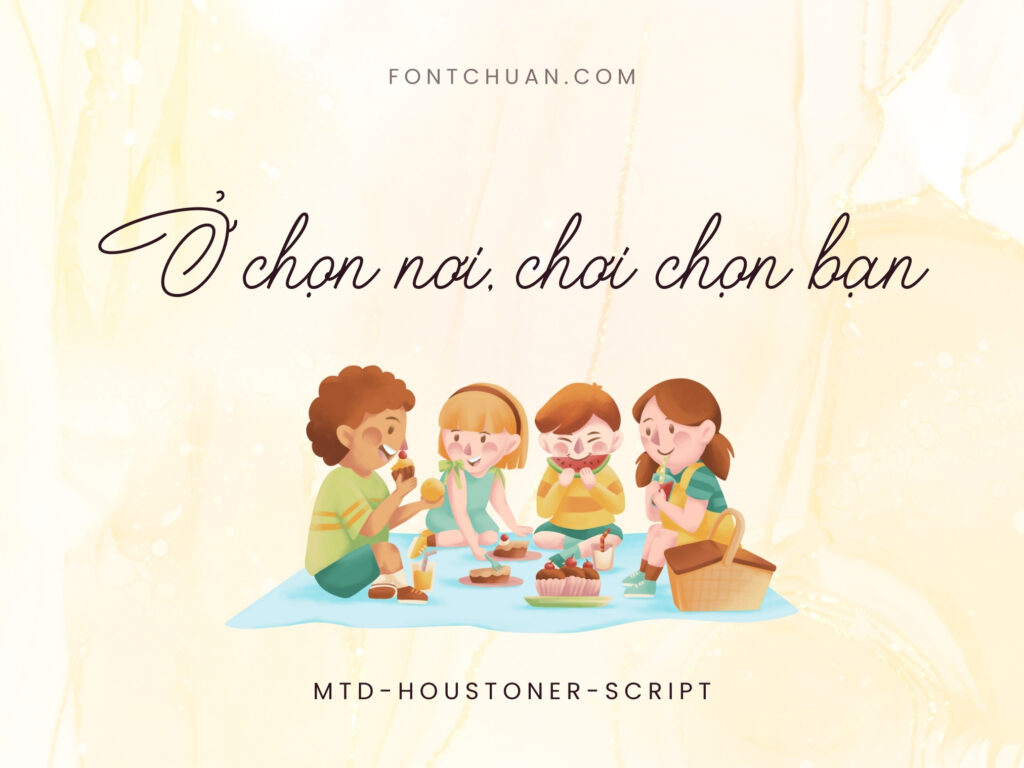
Font MTD Houstoner Script Việt Hóa
Font MTD Houstoner Script là một phông chữ viết tay thanh lịch, lấy cảm hứng từ kiểu chữ cổ điển, được thiết kế bởi Martype.Co và đã được Việt hóa bởi Mộc Hạ. Font này hỗ trợ đầy đủ tiếng Việt cùng hơn 90 ngôn ngữ khác, giúp mở rộng khả năng ứng dụng trong các thiết kế đa ngôn ngữ. Đây là một trong những phông chữ được cộng đồng thiết kế đánh giá cao và sử dụng trong nhiều dự án sáng tạo, đáp ứng nhu cầu đa dạng của người dùng.
MTD Houstoner Script nổi bật với các đường nét mềm mại và uyển chuyển, mang đến cảm giác tự nhiên và thân thiện. Font rất phù hợp cho các thiết kế logo, tiêu đề, bao bì sản phẩm, thiệp mời và các ấn phẩm đòi hỏi sự tinh tế và nghệ thuật. Các ngành nghề phù hợp bao gồm quảng cáo, giáo dục, công nghệ, thiệp cưới và ảnh cưới. Font này cũng lý tưởng cho các sự kiện như Tết, Giáng sinh, Valentine và các lễ hội khác.